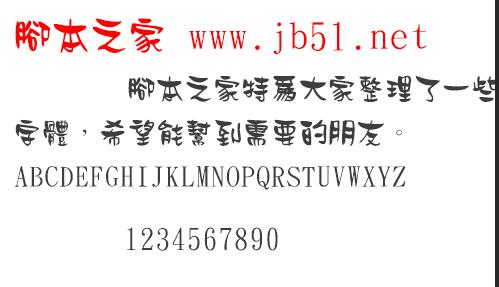
金梅浪漫原体国际码字体
金梅浪漫原体国际码字体是一款非常不错的艺术字体,该字体流畅自然,笔画圆润字迹秀气,艺术效果十分不错,具有强烈的视觉冲击力,从整体上看,更加的大气唯美,可以很好的应用于文本装潢、信息展示、网页设计、篆刻制模、数据制作、装潢设计、计算艺术设计、视觉设计、字帖等一切合法应用场景,有喜欢的朋友可免费下载收藏。